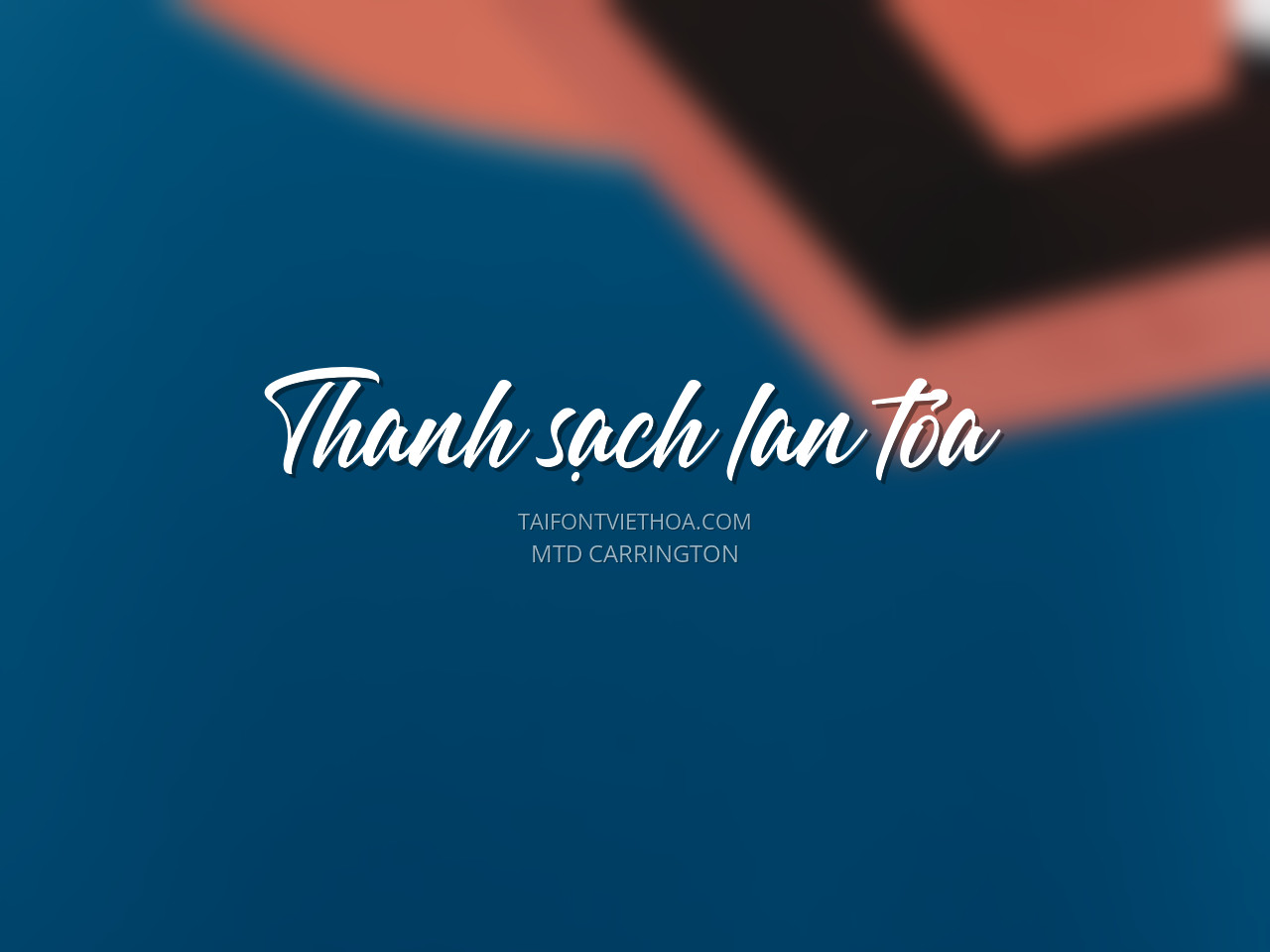
Font việt hóa MTD Carrington
Giới thiệu về font Carrington – Phong cách quý tộc cổ điển phương Tây
Carrington là một kiểu chữ viết tay mô phỏng thư pháp cổ điển, thường được xem là đại diện cho phong cách Anh quý tộc thế kỷ 18–19. Font được phát hành bởi các nhà thiết kế độc lập trên các nền tảng như DaFont, 1001Fonts, tuy không công bố rõ tác giả gốc. Carrington thu hút nhờ những đường nét bay bổng, ký tự uốn lượn mềm mại, phù hợp cho những dự án đòi hỏi sự sang trọng, cổ điển và hoài niệm. Font hỗ trợ tiếng Anh, một số ký tự mở rộng và thường được dùng trong các thiết kế kiểu phương Tây cổ điển.
Phiên bản Việt hóa của Carrington do Mộc Hạthực hiện đã được mở rộng đầy đủ bộ dấu tiếng Việt, giữ lại nguyên vẹn tinh thần thư pháp cổ của bản gốc. Đây là một trong những font được taifontviethoa.comtuyển chọn và chia sẻ cho cộng đồng sáng tạo trong nước, nhằm hỗ trợ những dự án mang tính chất hoài cổ, cao cấp hoặc mang tính cá nhân hóa mạnh.
Đặc điểm thiết kế ấn tượng và ứng dụng phù hợp của Carrington
Carrington mang phong cách thư pháp cổ điển, với các ký tự được thiết kế mềm mại, độ nghiêng lớn và nét chữ thanh mảnh uốn cong đặc trưng. Font bao gồm nhiều glyph trang trí (swashes), ligatures cổ điển và ký tự thay thế, giúp người dùng dễ dàng tạo ra những thiết kế mang cảm xúc quý phái, hoài niệm. Carrington mang đến cảm giác lãng mạn, cao sang, gợi nhớ đến những bức thư tay viết bằng mực nâu thời xưa.
Font này phù hợp cho các thiết kế như: thiệp cưới cổ điển, thư mời sự kiện cao cấp, logo mỹ phẩm thủ công, tiêu đề sách vintage, bìa tạp chí nghệ thuật, hoặc các sản phẩm in ấn theo phong cách retro – hoài cổ. Ngành nghề phù hợp gồm: sự kiện, thủ công mỹ nghệ, thời trang vintage, studio chụp ảnh, thiệp cưới, thương hiệu cá nhân hoặc sản phẩm mang bản sắc truyền thống phương Tây.